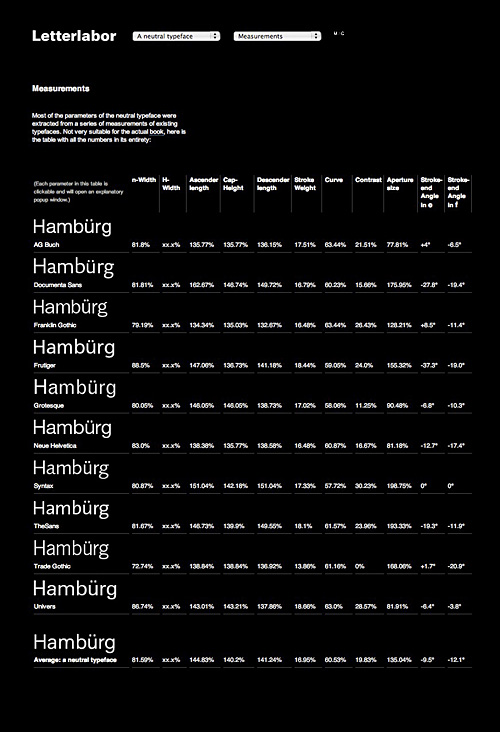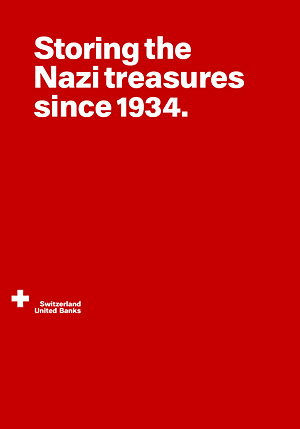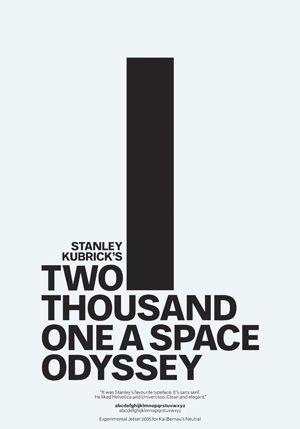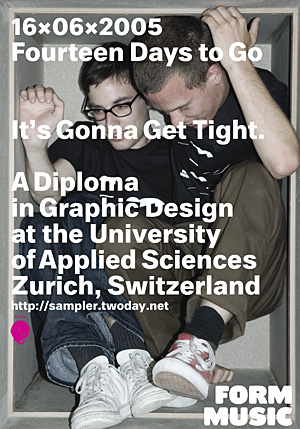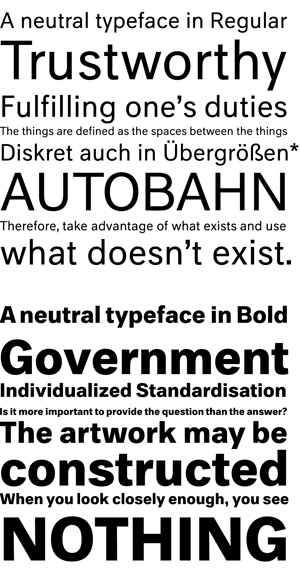
In Arbeit: Die Schrift ohne EigenschaftenKai Bernau studiert an der Schriftentwerferschmiede
schlechthin, The Royal Academy of Fine Arts in Den Haag. Seine
Abschlussarbeit widmet sich dem Thema »Neutralität im
Grafikdesign«, speziell in Typografie und Schriftgestaltung. Bernau
entwickelte eine maximal neutrale Schrift, indem er das mathematische Mittel aus
10 Sans-Serif-Schriften bildete, die bereits als weitgehend sachlich geltenden:
AG Buch, Neue Helvetica, Univers, Grotesque, Franklin Gothic, Frutiger, Trade
Gothic, Documenta Sans, The Sans und Syntax. Weiterlesen ...
![]() Aus dem programmatischen Einleitungstext der Diplomarbeit von Kai
Bernau:
»Kann eine Schrift ›neutral‹ sein? Gerade weil es Schriften geben soll, die ›neutraler‹ als andere sein wollen, wird der ursprüngliche Anspruch – die Idee der Neutralität – wieder zunichte gemacht. Zum Beispiel Helvetica. Da diese Schrift allgegenwärtig ist und als universell gilt – wobei alle Designer die Ansicht teilen, dass sie keinen Charakter habe –, wurde ihr im Laufe der Zeit genau die Eigenschaft zuteil, keine Eigenschaft zu haben. Das in Amsterdam angesiedelte Design-Kollektiv Experimental Jetset beschreibt Helvetica als überhaupt nicht neutral, stattdessen als selbstbezogen. Der Mythos einer Helvetica als neutrale Schrift sei das Ergebnis einer sich selbst erfüllenden Prophezeiung. Dabei ist es egal, ob der Helvetica-Nutzer sich dieses Mythos bewusst ist oder tatsächlich glaubt, eine neutrale Schrift einzusetzen. Neutralität anzustreben bedeutet tatsächlich einen starken Wert zu kommunizieren, namentlich sich selbst: So wie man eine treffende, ausdrucksstarke Schrift wählt, um beim Leser eine bestimmte Assoziation auszulösen, soll eine neutrale Schrift solche Assoziationen unterdrücken. Sie soll den Text zwar unterstützen, aber keine ›angemessene‹ Atmosphäre hinzufügen. Im Mittelpunkt steht ausschließlich der Text. Diesen leicht zugänglich zu machen und die Gedanken des Lesers auf den Inhalt zu lenken, und nicht auf den Kontext drumherum, ist die Aufgabe einer neutralen Schrift.« ![]() Schriftmuster der beiden Neutrality-Schnitte von Kai Bernau Doch wie kommt man zu ›der neutralsten Schrift‹? Zunächst durch das Vergleichen und »Aussortieren« von Schriften. Anschließend suchte sich Kai Bernau 10 als sachlich eingestufte Schriften heraus (AG Buch, Neue Helvetica, Univers, Grotesque, Franklin Gothic, Frutiger, Trade Gothic, Documenta Sans, The Sans und Syntax), die er mathematisch vermaß: ![]() Messtabelle, veröffentlicht auf Kai Bernaus Internetseite Letterlabor So entstanden die ersten beiden Neutrality-Schnitte: Roman und Bold. Beide sind noch nicht komplett ausgebaut. Demnächst widmet sich Kai Bernau den dazugehörigen Italics. Den Kern seines Diplomprojekts bildet ein Forschungsbuch, das die Entwicklung der Begriffsbildung von Neutralität darstellt – nach eine langen Phase der Meditation und Diskussion. Zu Bernaus Beratern gehören Daniel van der Velden (NL), Experimental Jetset (NL), Uwe Loesch (DE), Bernd Kuchenbeiser (DE) und Helmut Schmid (CH/JP). Gerade die Gespräche mit den Mentoren führten schließlich zur Definition des Neutralitätsbegriffs in der Typografie. Weitere Informationen zur Diplomarbeit finden sich auf seiner Internetseite: Schriftmuster Neutralschrift Regular Schriftmuster Neutralschrift Bold Gesamtschriftmuster als PDF Messtabelle der 10 Schrift-Inspirationen Leseprobe Neutrality-Buch Übersicht der Poster ![]() Mit einer Serie von Postern überprüft Kai Bernau die Neutralität seiner Schrift ... ![]() ... fügt sie dem Text tatsächlich keine eigene Note bei ... ![]() ... ist sie stark und neutral genug im Zusammenspiel mit einem Foto? Herausgegeben: Fr - November 11, 2005 at 08:46 vorm. | |